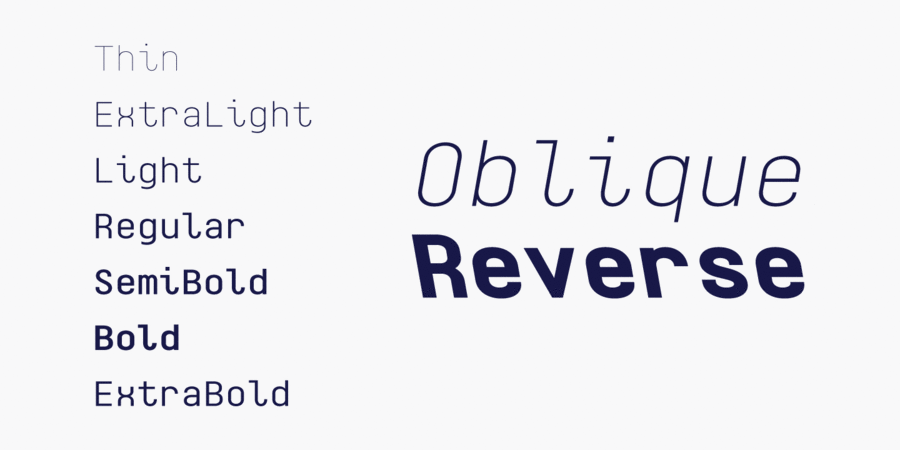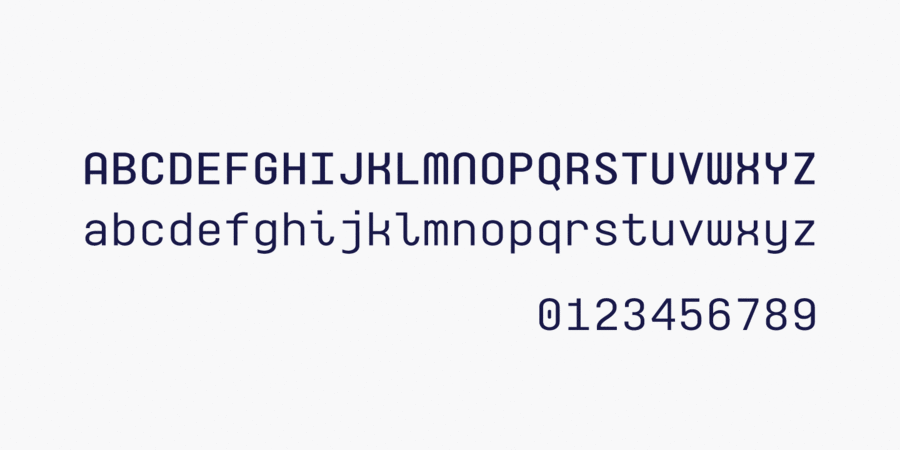
Опис гарнітури MonospacelandЦе круглий моноширинний шрифт з 7 насиченостями, багатою мовною підтримкою (включно з кирилицею), капітеллю та деякими альтернативами з подвійною шириною для додаткових розваг. Сімейство включає нахилені та зворотно нахилені версії, всього 21 накреслення. Крім того, в наборі є двовісний варіативний шрифт, що дозволяє встановлювати довільну жирність і кут нахилу. Шрифт розробив Олег Ліщук у 2020 році.
Асоціації з сімейством шрифтів MonospacelandОсобистість і характер гарнітури:
точний, рівний, переконливий, стабільний, твердий, надійний, сильний, стійкий, індустріальний, техногенний, статичний, міський, автоматичний, урбаністичний, сталевий, міцний, логічний, практичний, штучний, холодний, машинний, інженерний, важкий, залізний, креслярський, архітектурний, впевнений, космічний, футуристичний, технічний, якісний, доступний, чіткий, комп'ютерний, зрозумілий, космополітичний, прямий, грайливий, гладенький, оригінальний, модний, молодіжний, дзвінкий, позитивний, музичний, яскравий, помітний, елементарний, прозорий, тонкий, мінімалістичний, дротяний, легкий, худий, неоновий, чистий, ясний, лаконічний, делікатний, прохолодний, електронний, іронічний, глобалізований, глобалістічний, свіжий, Простий
техніка, прилад, промисловість, інструмент, архітектура, наука, дизайн, Місто, урбаністика, інженер, автоматика, космос, ракета, супутник, конструктор, технології, креслення, архітектор, фантастика, гра, шутер, електроніка, авто, паливо, кіно, код, IT, айтішник, комп'ютер, програмування, айті, залізо, коворкінг, робот, рентген, хакер, комп'ютерна гра, телебачення, шоу, зореліт, дискотека, нічний клуб, вечірка, бар, гаджет, девайс, чистота, АСМР, інтер'єр, астрономія, небо, аквадискотека Гарнітура асоціюється з віком: